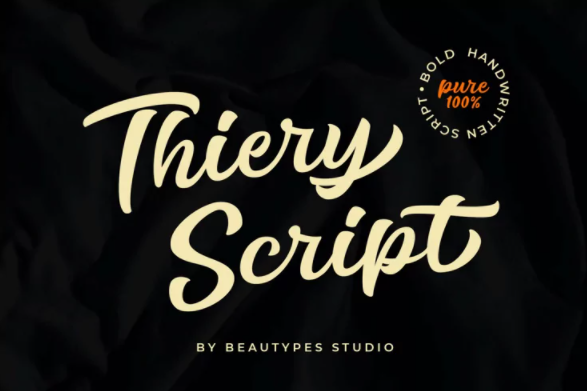
Thiery Script - это потрясающий шрифт, удивительный вариант для проектов брендинга и логотипов. Этот шрифт производит впечатление современного, модного и элегантного дизайна. Классический шрифт идеально подходит для тех, кому нужен шрифт для логотипов, одежды, приглашений, брендинга, упаковки, рекламы и т.д. Этот шрифт включает в себя прописные и строчные буквы, знаки препинания, символы и цифры, стилистический набор, лигатуры и т.д., а также поддерживает многоязычность и уже закодирован PUA.